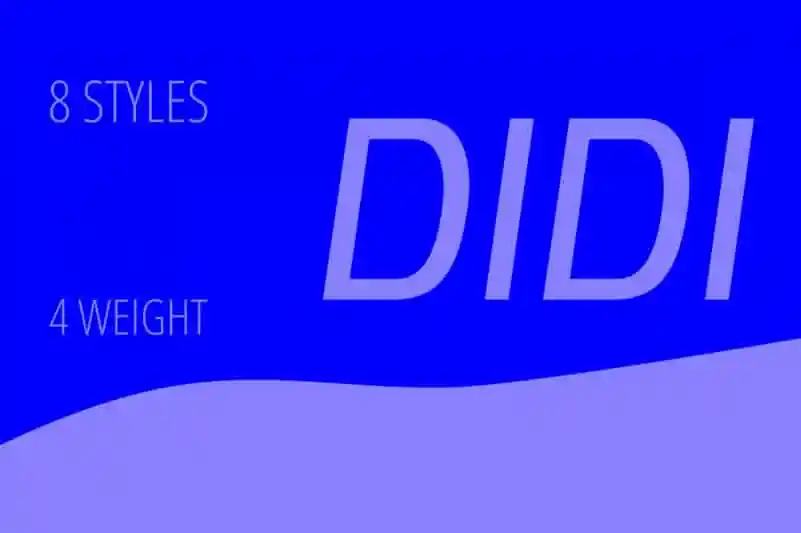
Didi Sans Serif Font – Fonte Grátis
Didi Sans Serif Font
A Didi Sans Serif é uma tipografia sans serif com contraído baixo e espaçoso counters. A sua elegância e simplicidade são características marcantes desta fonte, que vem em três tamanhos de uma seleção de oito estilos. Perfeita para temas simples de design e um toque sofisticado. Designada pelo próprio Arief Rochman na plataforma 99designs, a Didi Sans Serif se destaca pela sua disposição limpa e minimalista. Com seu x-height grande e counters espessos, esta fonte combina bem em qualquer tipo de design contemporâneo. Seja para criar um projeto de marca ou simplesmente para adicionar um toque moderno aos seus materiais gráficos, a Didi Sans Serif é uma escolha ideal.